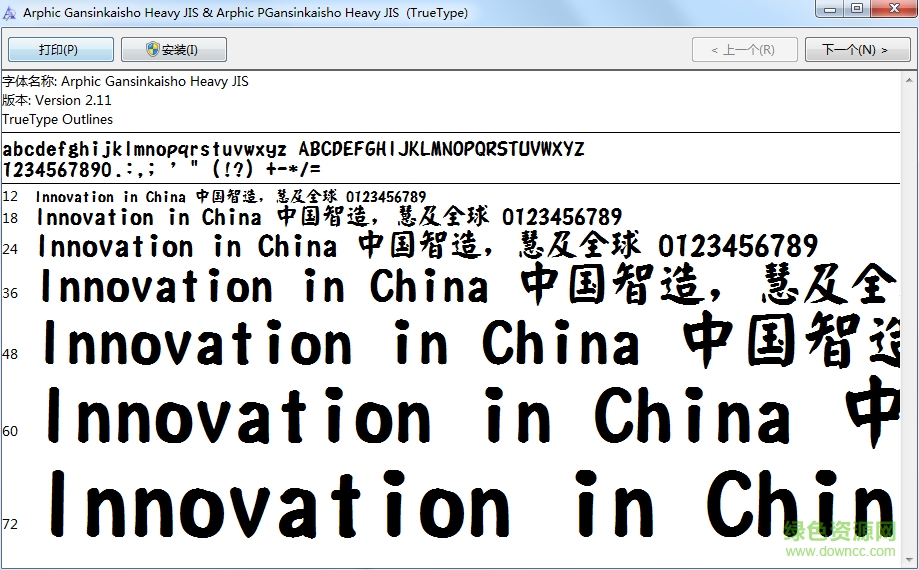
顏真卿楷書字體是著名唐朝政治家的獨門書法字體,顏真卿書法造詣極高與王羲之啟明,字跡大氣灑脫,正氣飄逸,喜歡上網(wǎng)朋友歡迎來綠色資源網(wǎng)下載使用哦!
顏真卿的書法,號稱顏體,有他獨特的風(fēng)格和筆法。他所留下的碑帖很多,后世的書法家認(rèn)為從他的一些碑帖中可以找到「圓筆」的痕跡,和其他書法家的「方筆」不同。
他的書法,既有以往書風(fēng)中的氣韻法度,又不為古法所束縛,突破了唐初的墨守成規(guī),自成一格,稱為“顏體”。宋歐陽修評論說:“斯人忠義出于天性,故其字畫剛勁獨立,不襲前跡,挺然奇?zhèn)ィ兴破錇槿?。宋朱長文《續(xù)書斷》中列其書法為神品?!辈⒃u說:“點如墜石,畫如夏云,鉤如屈金,戈如發(fā)弩,縱橫有象,低昂有態(tài),自羲、獻(xiàn)以來,未有如公者也?!?/p>